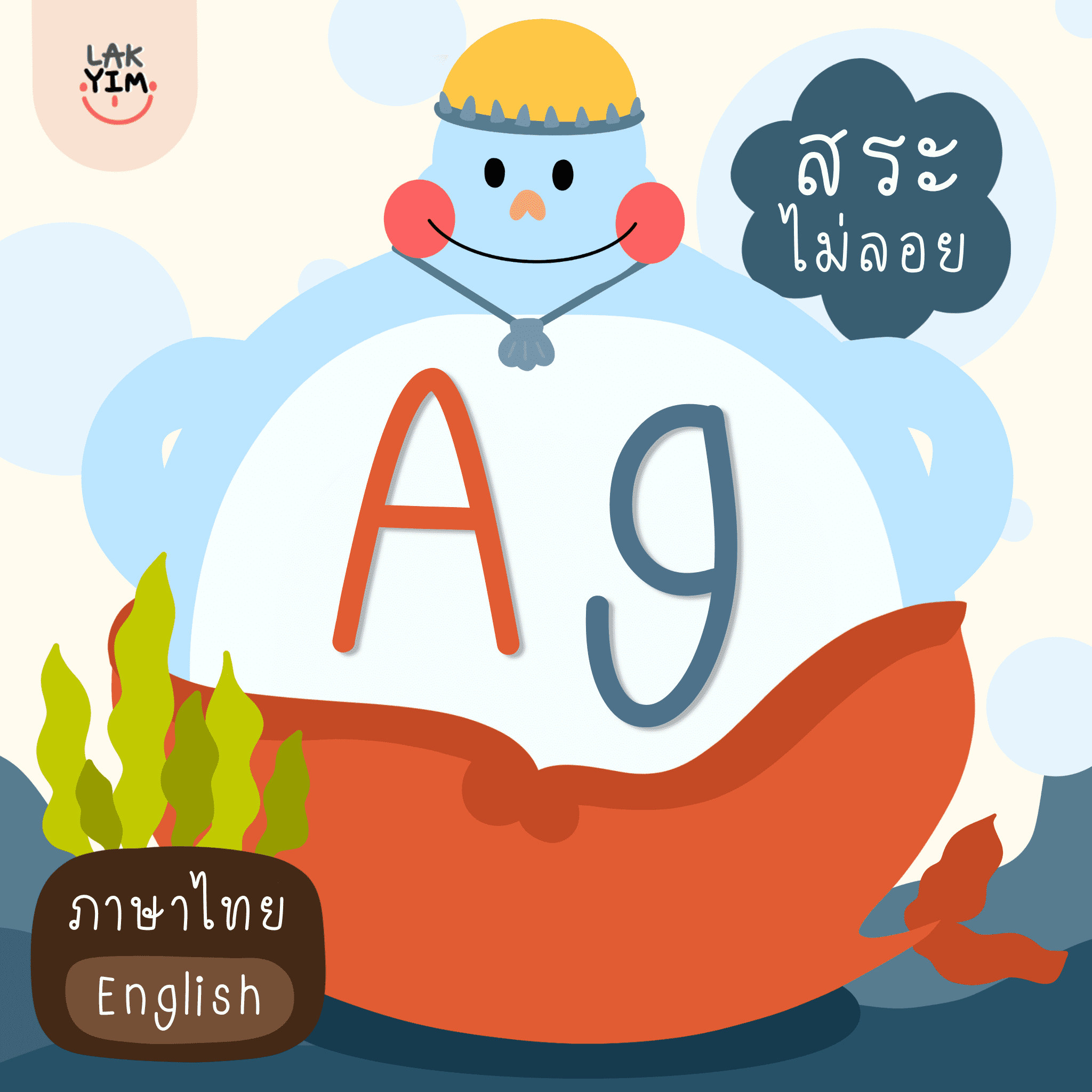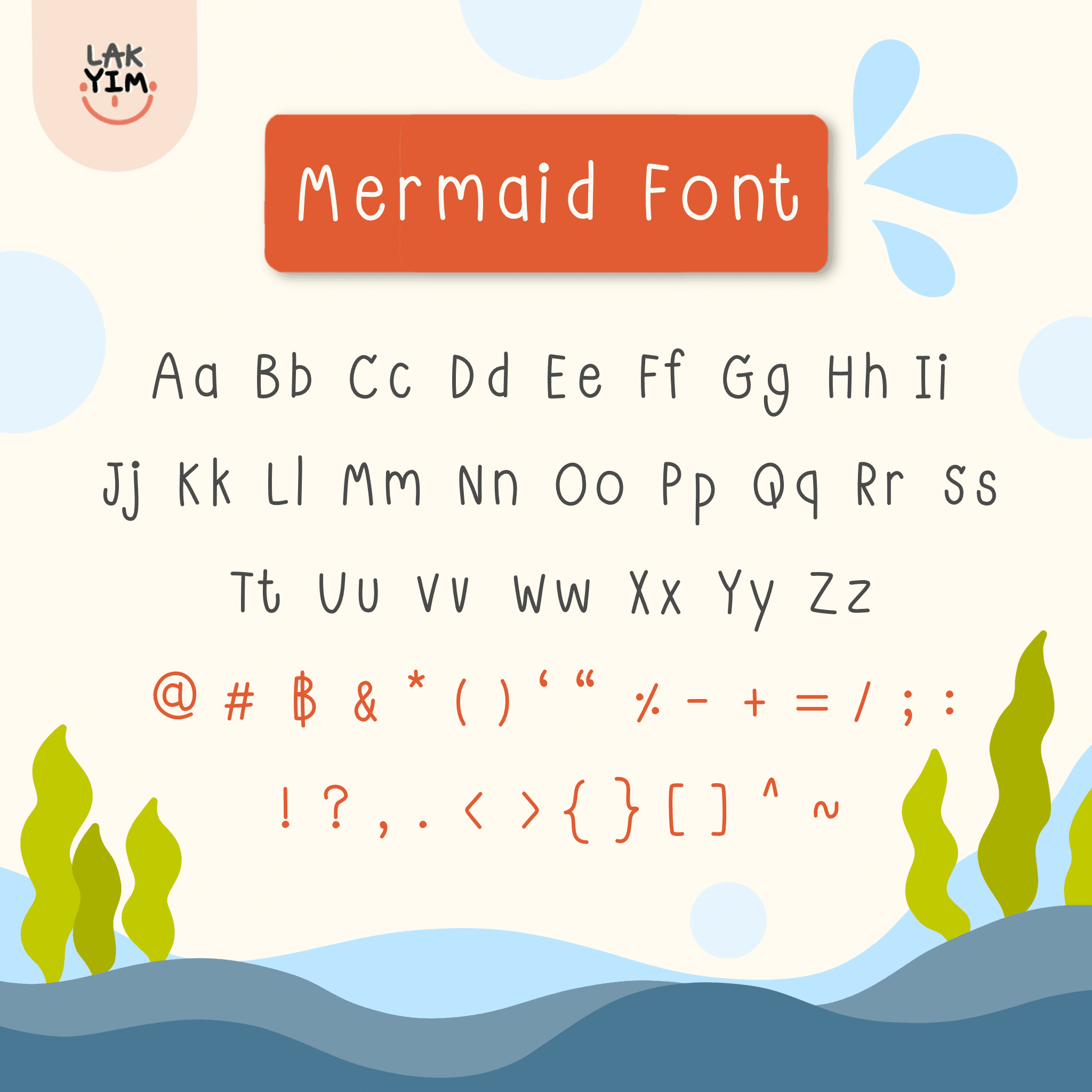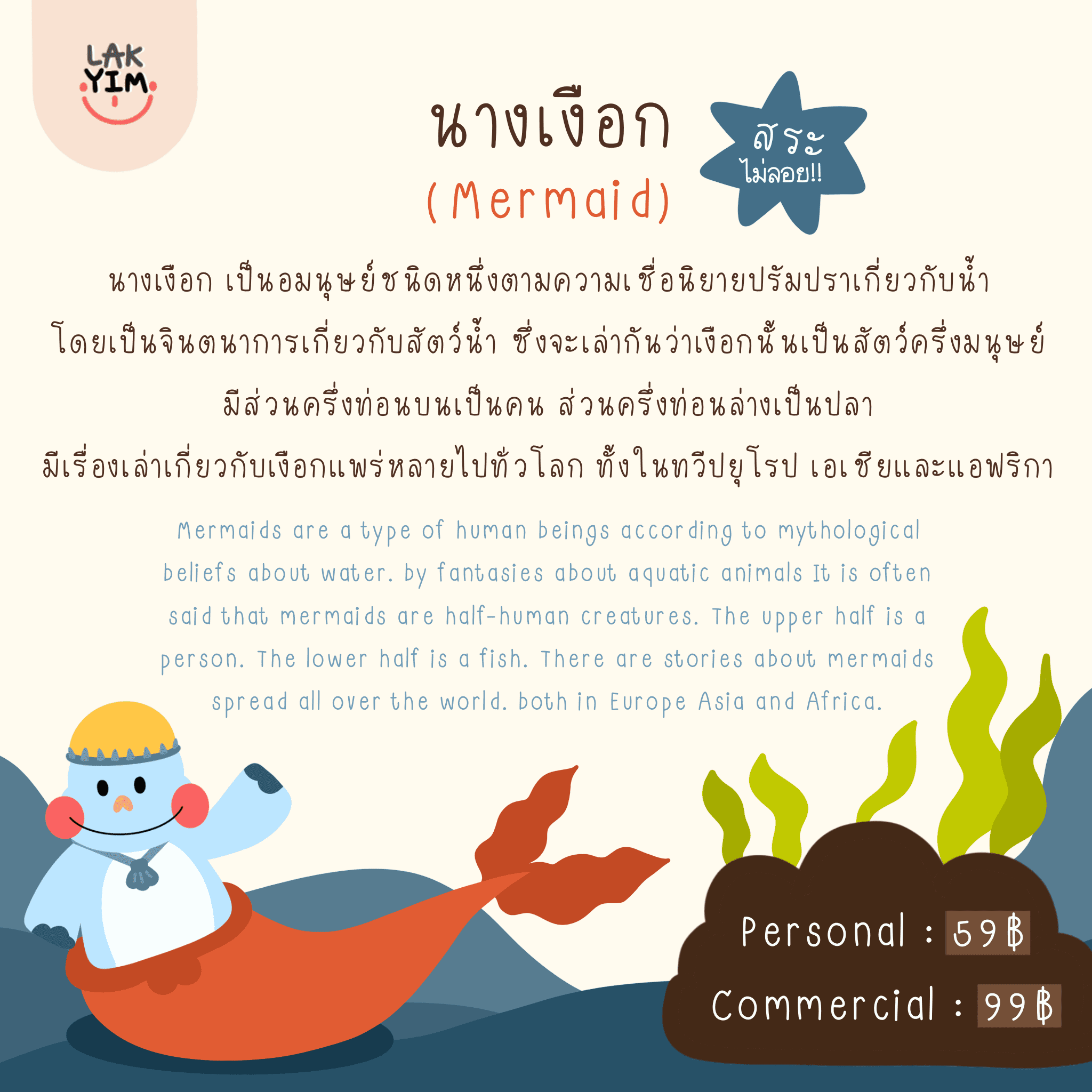
ฟอนต์ลายมือแบบตัวบาง มีความน่ารักกุ๊กกิ๊ก อ่านง่าย สบายตา เหมาะกับการเอาไปใช้เขียนบันทึก หรือทำชีทสรุปอย่างมาก
📍สระ ไม่ ลอย ‼️‼️
– มีทั้งภาษาไทยและภาษาอังกฤษ